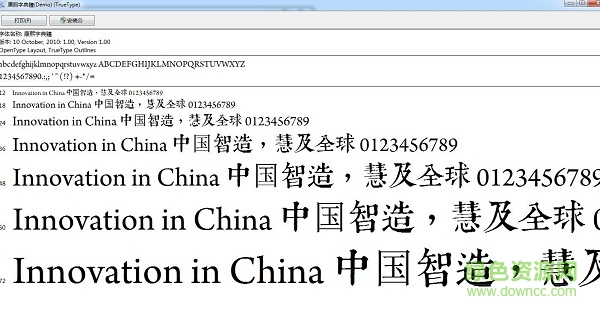
康熙字典體demo
tpldkhangxidictdemo是什么字體?tpldkhangxidictdemo字體又叫康熙字典體(demo)字體,該字體強調(diào)傳承感,用筆收斂,字形端正,沒有過多的修飾,需要的朋友歡迎免費下載!
康熙字典介紹
1.《康熙字典》是張玉書、陳廷敬等三十多位著名學(xué)者奉康熙圣旨編撰的一部具有深遠影響的漢字辭書。
tpldkhangxidictdemo
2.《康熙字典》吸收了歷代字書編纂的有益經(jīng)驗,又集中了傳統(tǒng)字書編纂中規(guī)模最大的30人編寫隊伍,加上是御敕纂修,問世后影響巨大。
3.《康熙字典》收字多,字之別體、俗寫均錄,其文字音義書證廣為引用,其體例成為后出字書的藍本。